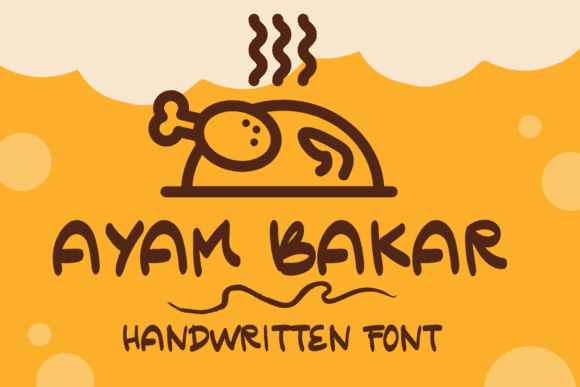
Fuente Ayam Bakar para manualidades, logotipos y proyectos de impresión
Añade un toque de encanto y fantasía a tus proyectos con la fuente Ayam Bakar . Cálida, romántica y alegre, esta fuente transforma tus ideas en obras de arte.
- Diseño encantador y caprichoso.
- Perfecto para proyectos cálidos y románticos.
- Infinitas variaciones para explorar